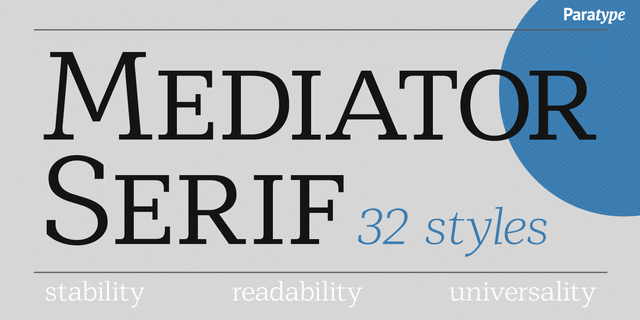
Mediator Serif — спокойная и уравновешенная современная антиква, которая идеально сочетается с гротеском Mediator по рисунку и пропорциям. Шрифт хорошо работает как в сплошном тексте, например, в деловой литературе и периодике, так и в коротких текстах, упаковке и брендинге. Гарнитура состоит из 32 начертаний: 8 прямых и 8 курсивных достаточно широких пропорций, от Thin до Black, и 8 зауженных начертаний со своими курсивами. Минускульные цифры и капитель во всех начертаниях служат приятным дополнением к знаковому составу шрифта. Шрифт спроектирован Манвелом Шмавоняном при участии Александра Любовенко и выпущен компанией ПараТайп в 2017 году.
деликатный, чистый, легкий, худой, прохладный, тонкий, современный, ясный, ровный, понятный, качественный, невесомый, прозрачный, городской, точный, четкий, хрупкий, логичный, воздушный, стеклянный, острый, проволочный, статичный, дорогой, свежий, умный, спокойный, универсальный, простой, нейтральный, средний, обычный, деловой, уравновешенный, космополитичный, ненавязчивый, стандартный, умеренный, техничный, прямой, глобализированный, глобалистичный, монотонный, объективный, неброский, прагматичный, практичный, оптимальный, твердый, невыразительный, доверительный, комфортный, строгий, серьезный, стабильный, надежный, устойчивый, удобный, вежливый, безразличный, равнодушный, убедительный, доступный, авторитетный, уверенный, важный, правильный, самостоятельный, ответственный, западный, холодный, модный, значительный, обязательный, солидный, сильный, тяжелый, урбанистический, грубый, мотивирующий, чертежный, инженерный, мощный, плотный
диета, гигиена, город, здоровье, чистота, наука, образование, математика, статистика, адвокат, финансы, деньги, юрист, банк, химия, физика, бизнес, лекарство, инвестиции, медицина, рентген, власть, суд, экономика, новости, конструктор, инструмент, станок, техника Стилистика: